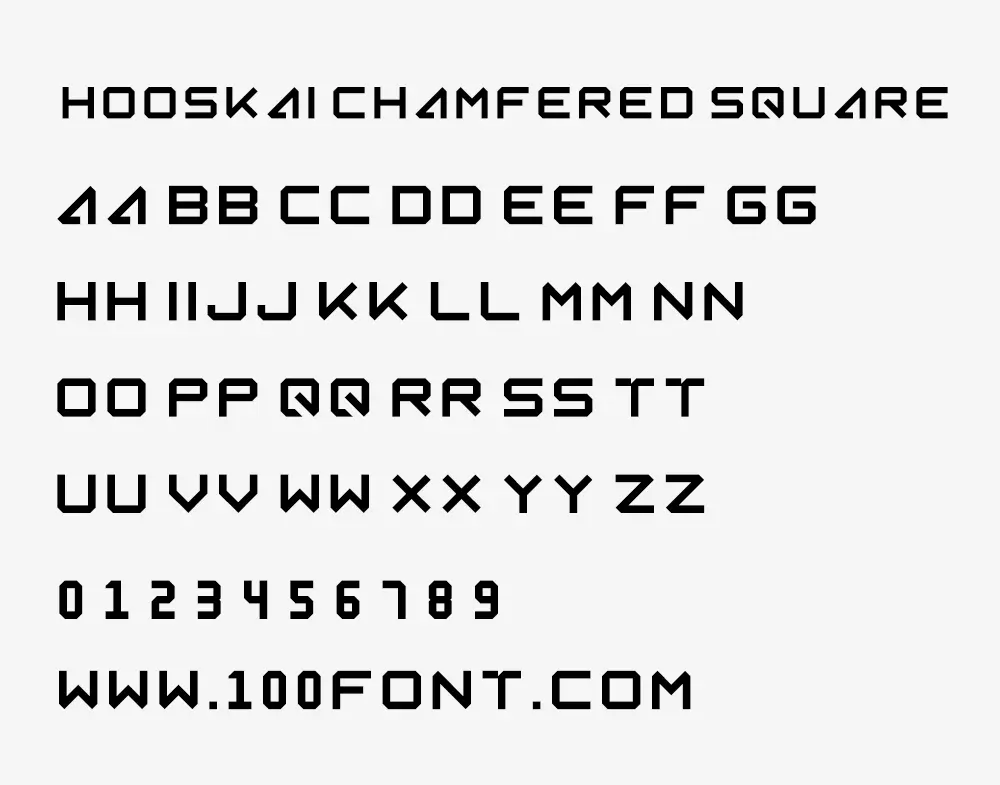
哈嘍啊,我是斯凱。 這個字體字如其名,這是我畫的一個被削了角、方方的字體,沒甚麼好介紹的。
Hey there, I'm Husky. This font, as the name suggests, is a square-shaped font with chamfered edges that I designed. There's not much else to say about it.
目前已支援(Unicode):基本拉丁字母、部分拉丁字母補充-1、部分拉丁字母補充-A、部分拉丁字母補充-B、大部分西裡爾字母。
Currently supported (Unicode): Basic Latin, some Latin 1 Supplement, some Latin Extended-A, some Latin Extended-B, and some Cyrillic.